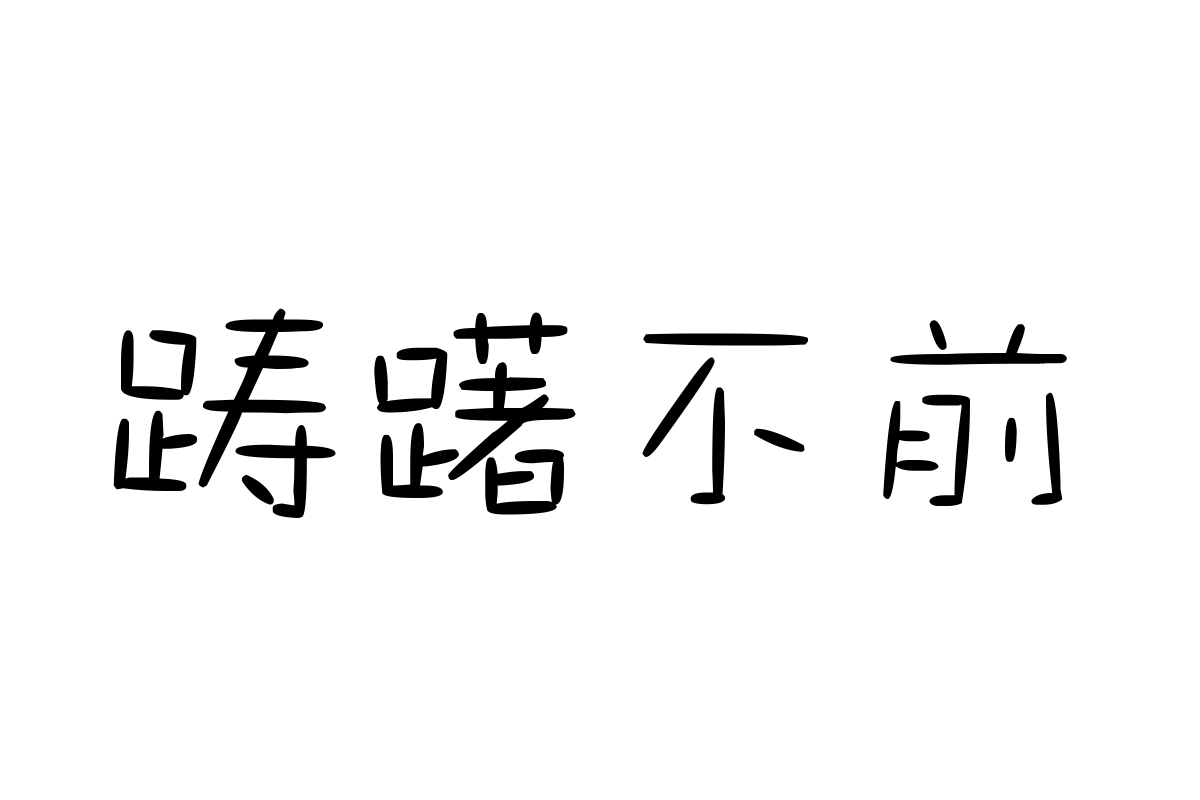
文道火柴体是一种简洁、现代的中文字体。它由设计师精心打造,旨在为用户提供一种清晰、易读的视觉体验。
该字体的特点包括:
– 优雅而流畅的笔画,使得文字看起来既美观又易于阅读。
– 精心设计的字形结构,使得每个字符都能准确地传达其意义。
– 适用于各种场景,如广告、海报、网页设计等。
总之,文道火柴体是一种非常适合现代设计的中文字体,无论是用于商业还是个人项目,都能让你的文字脱颖而出。